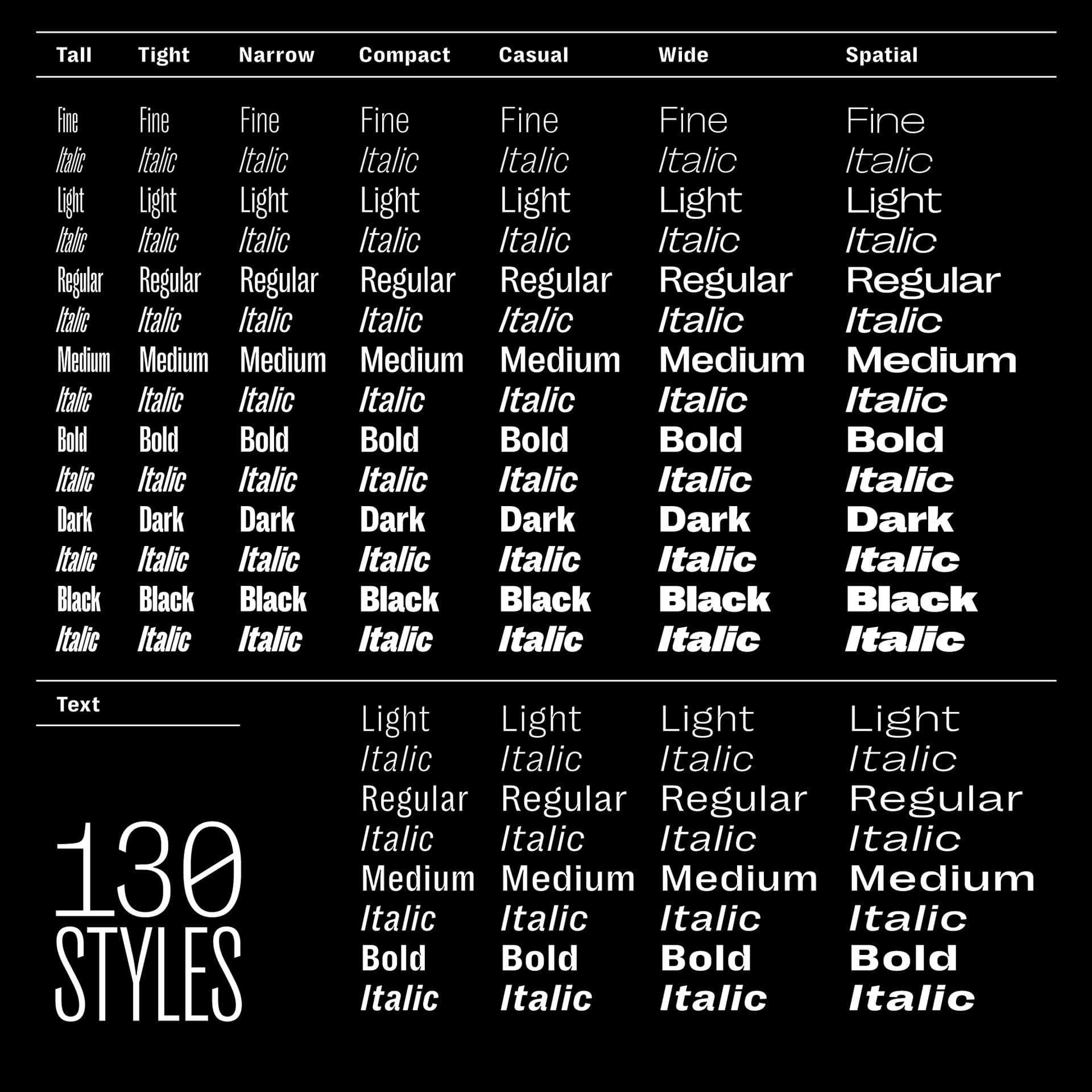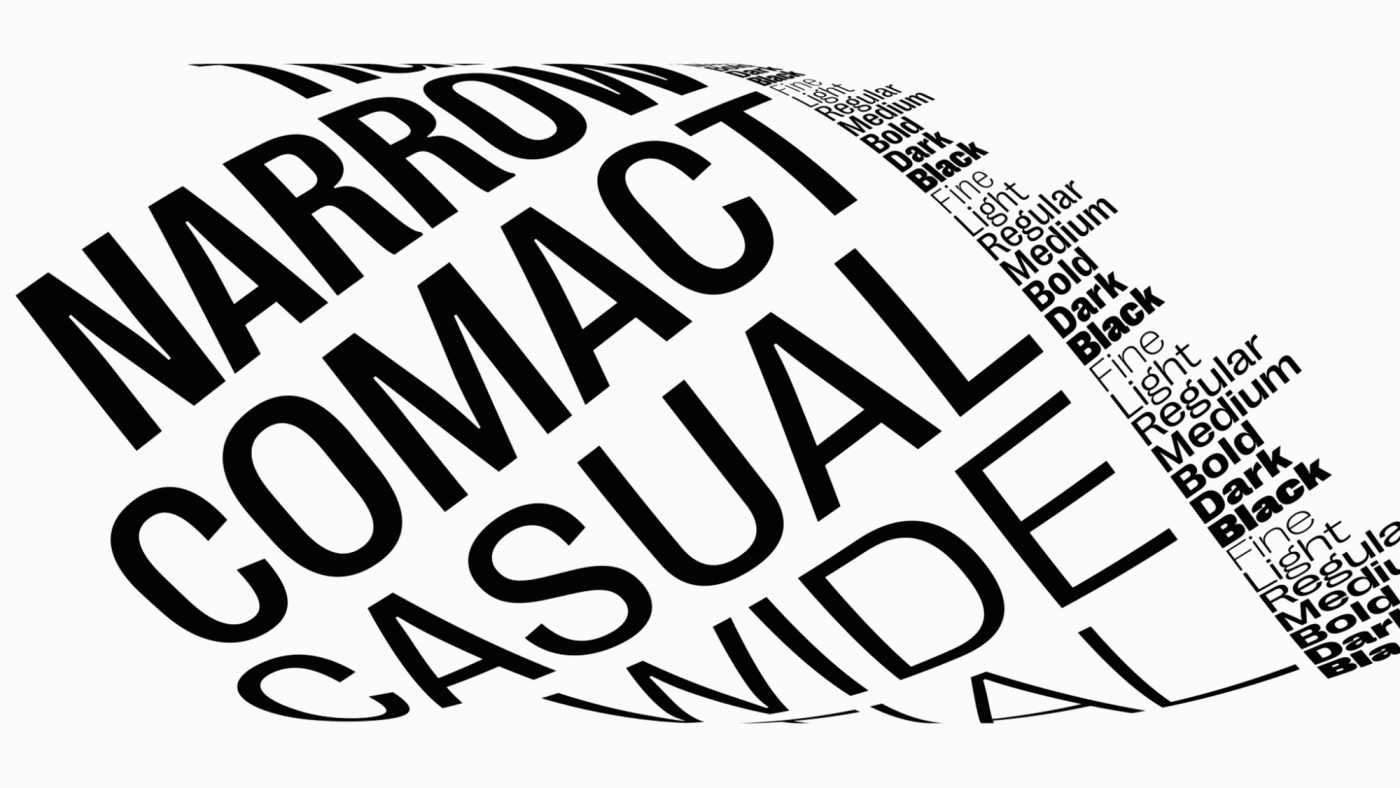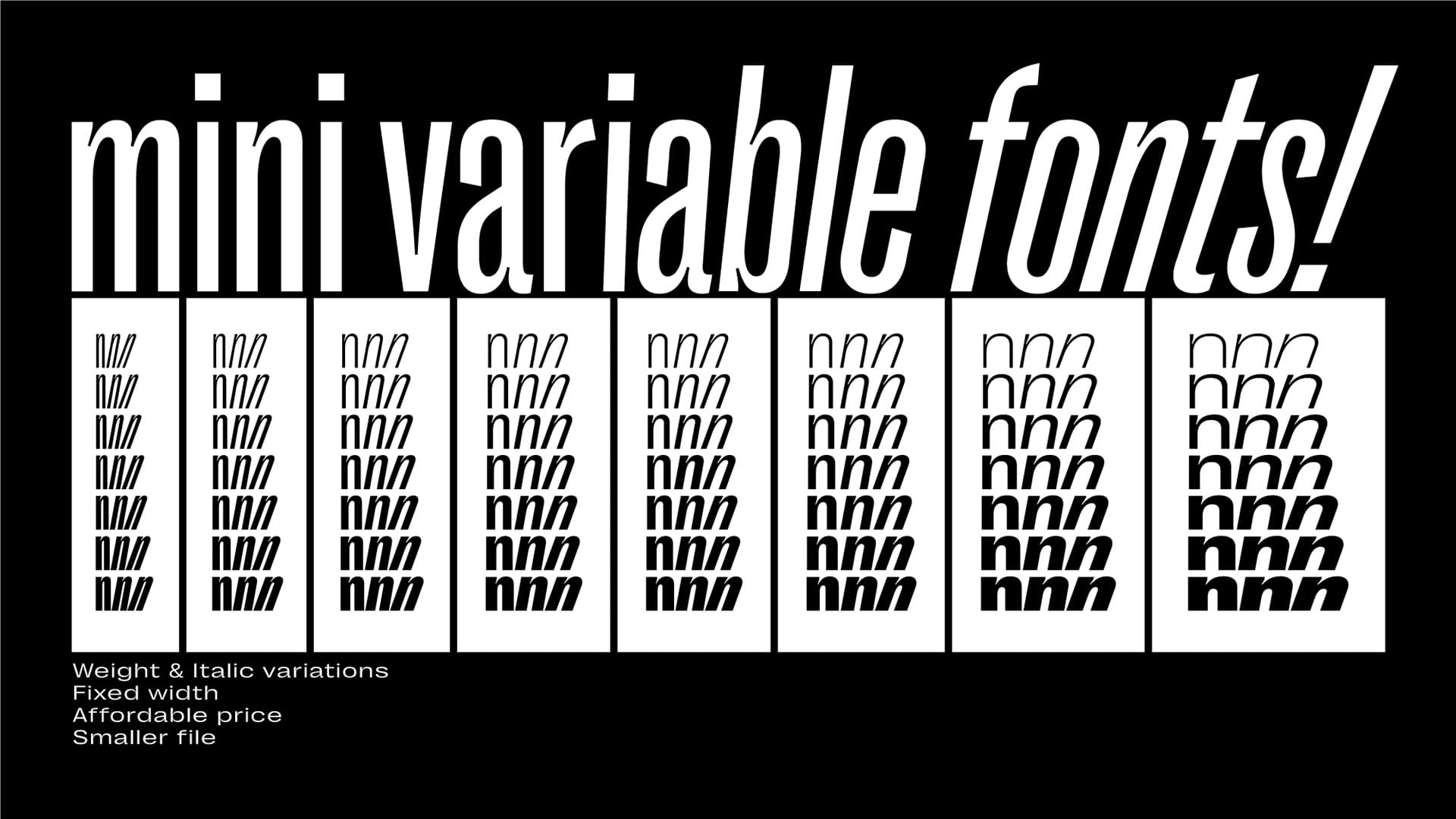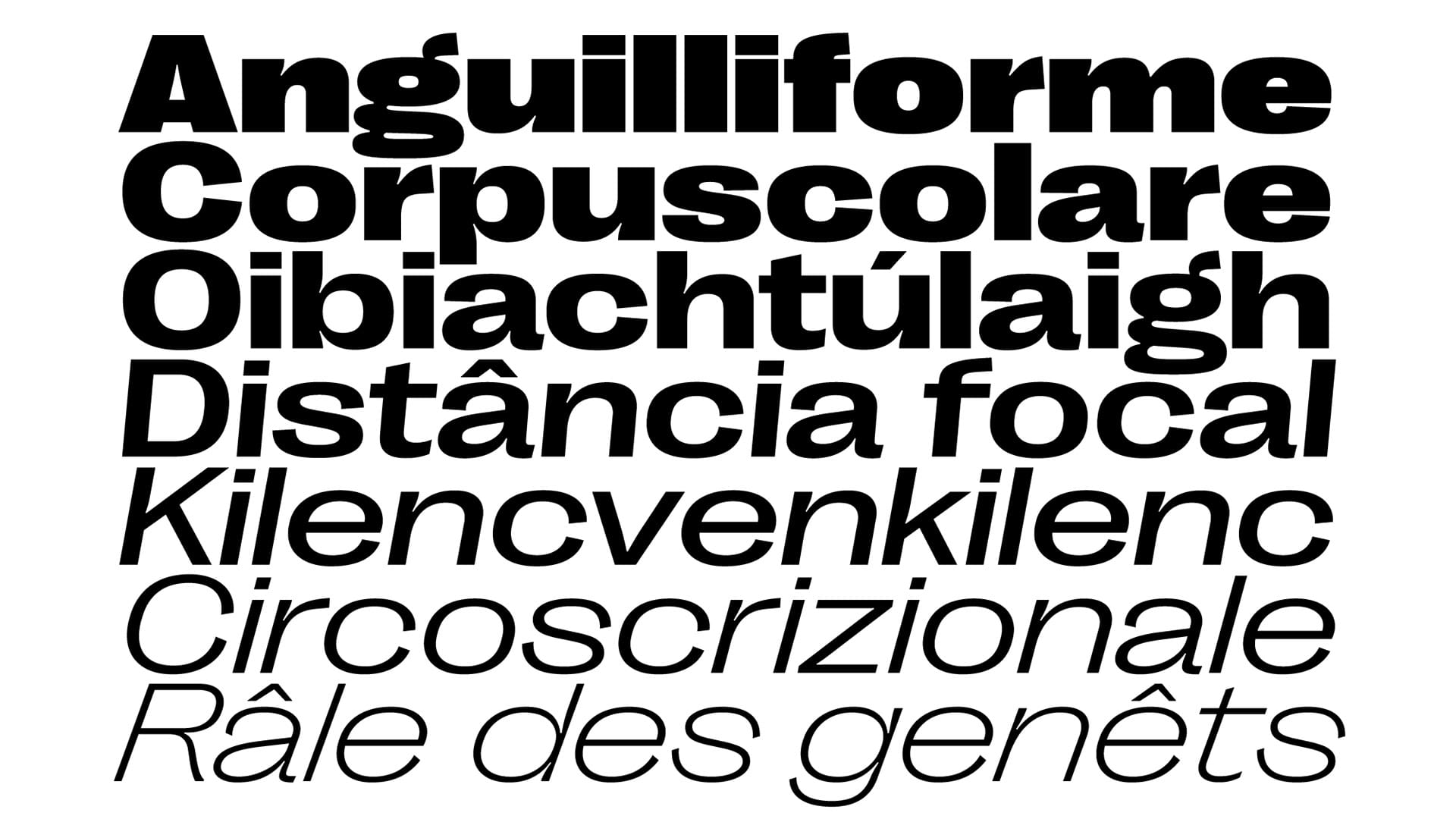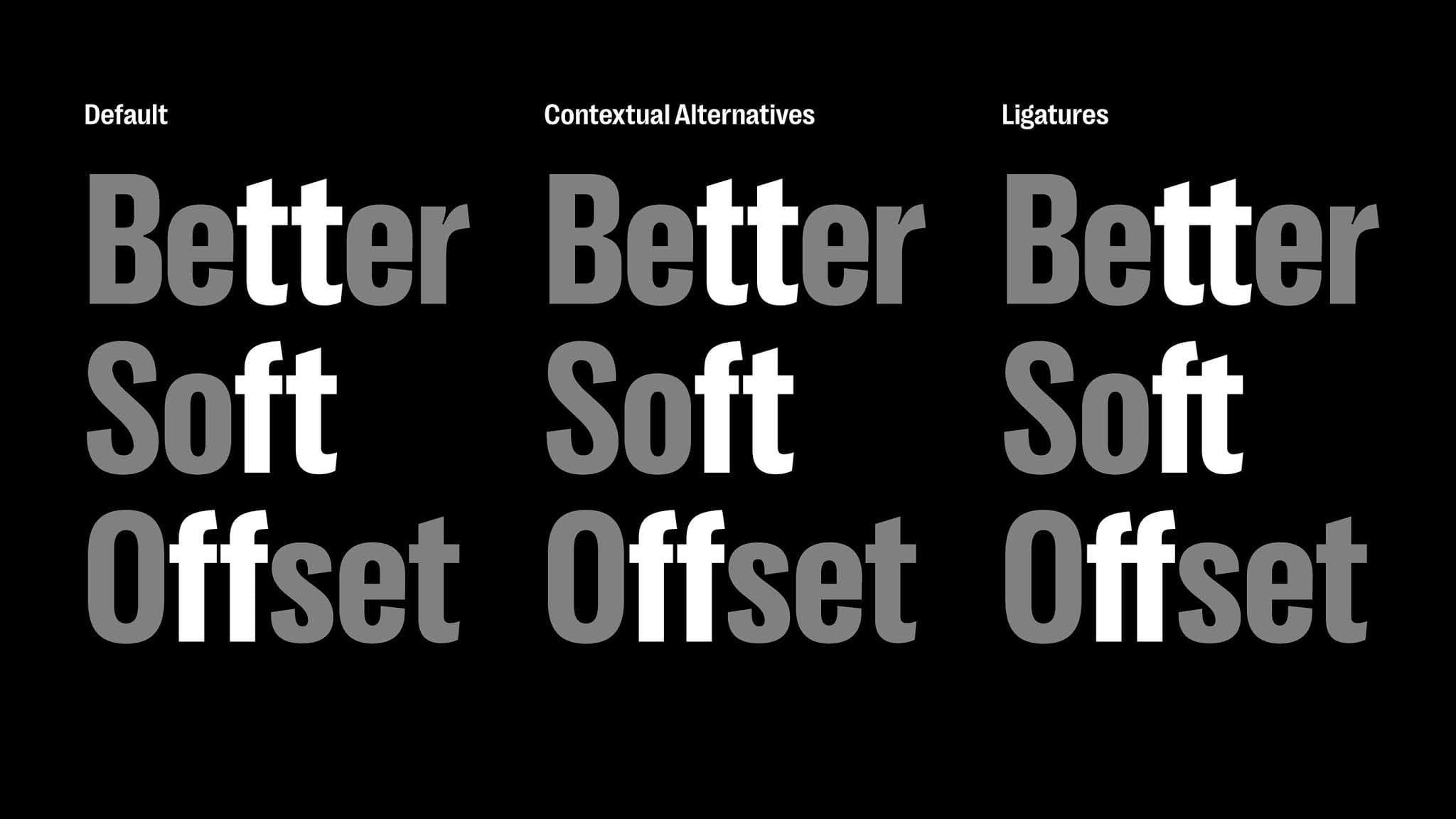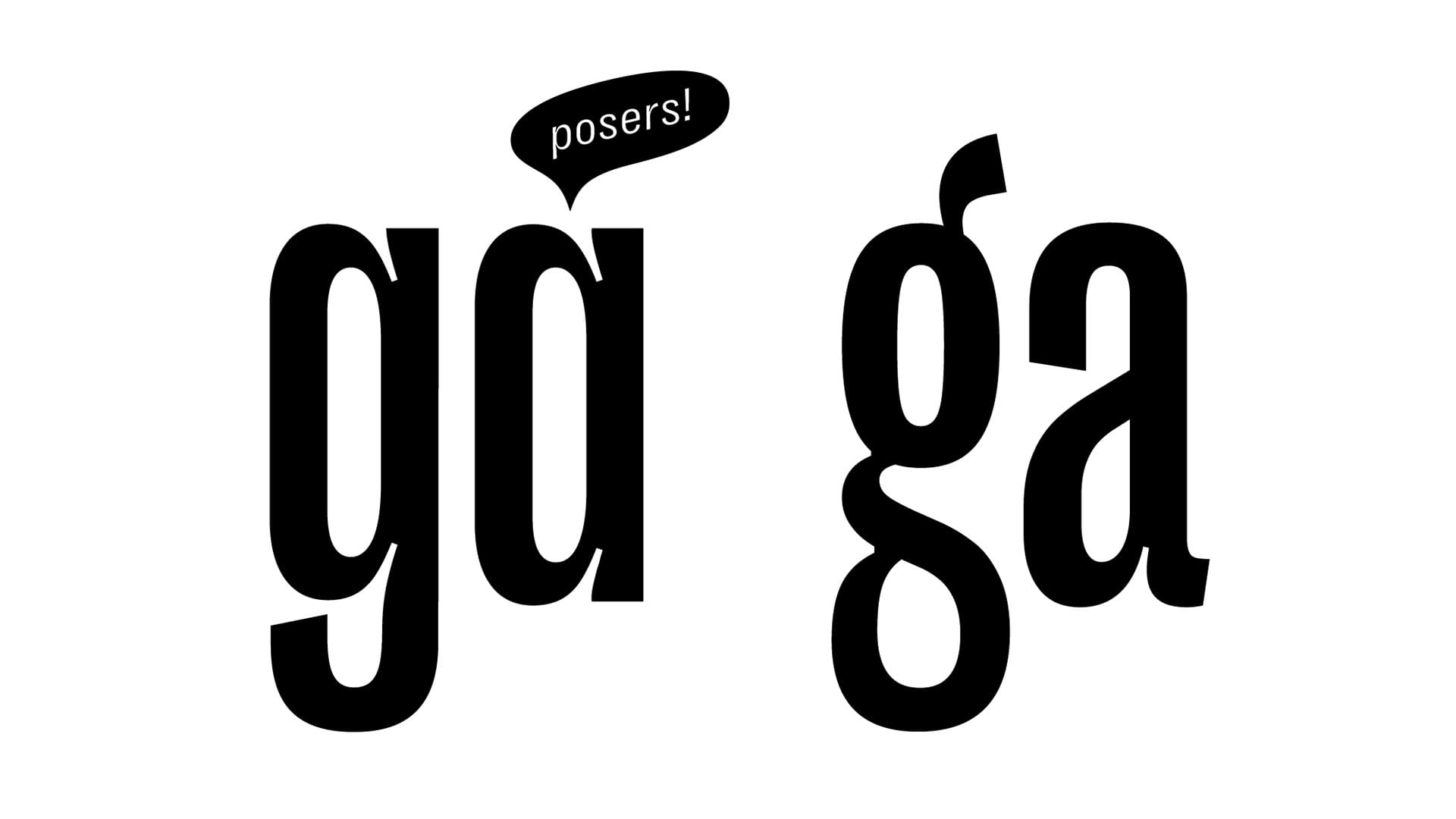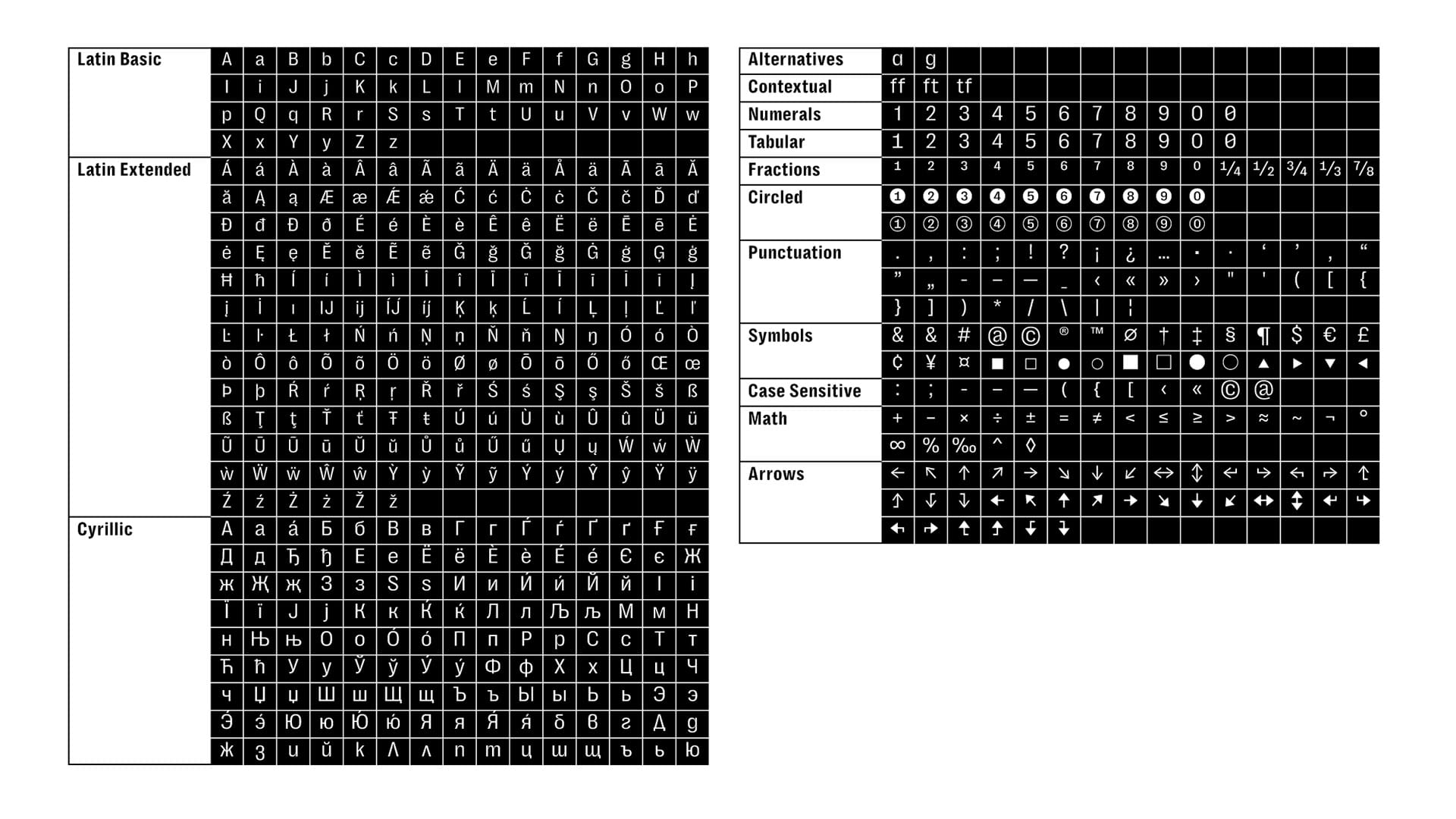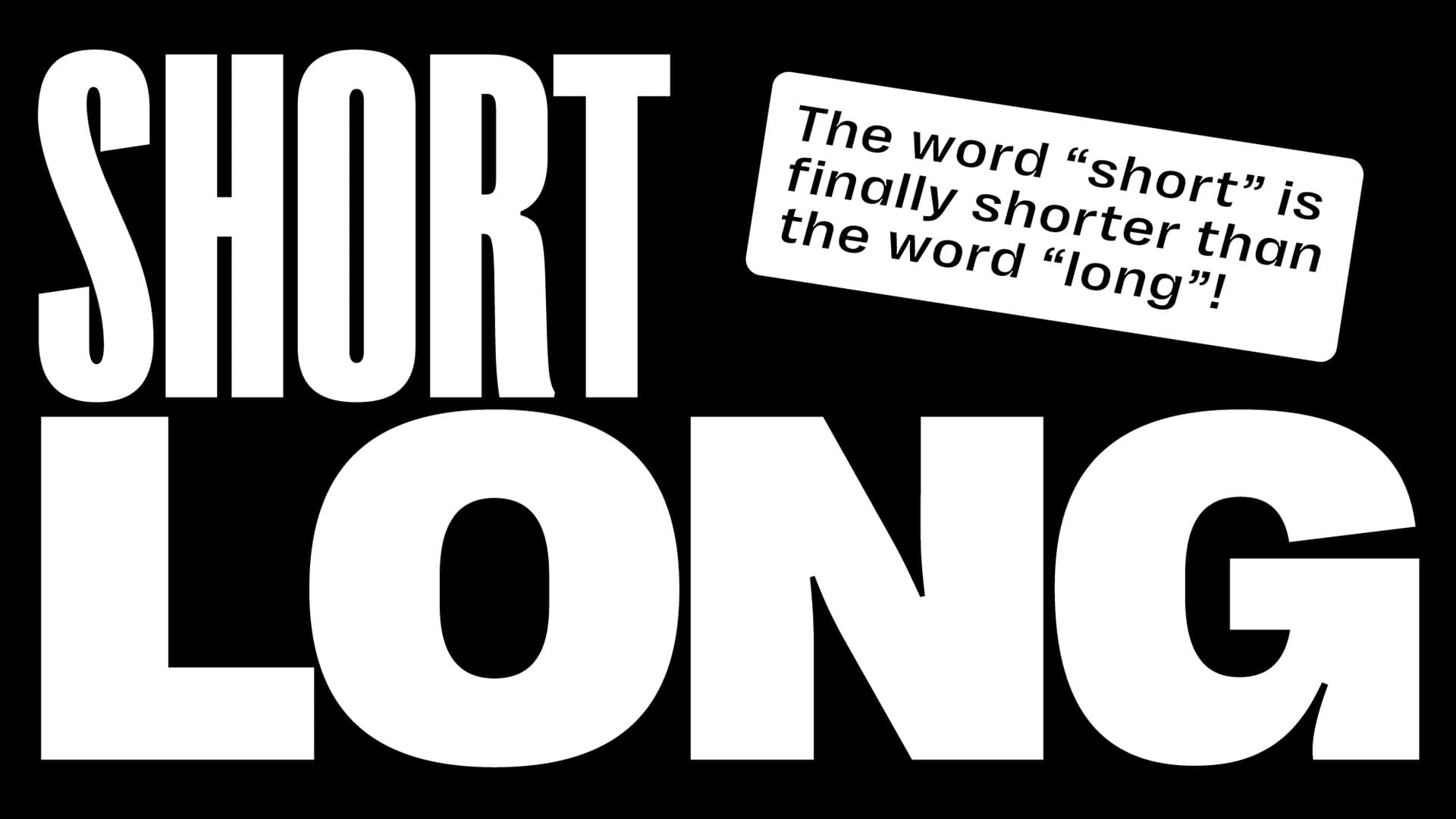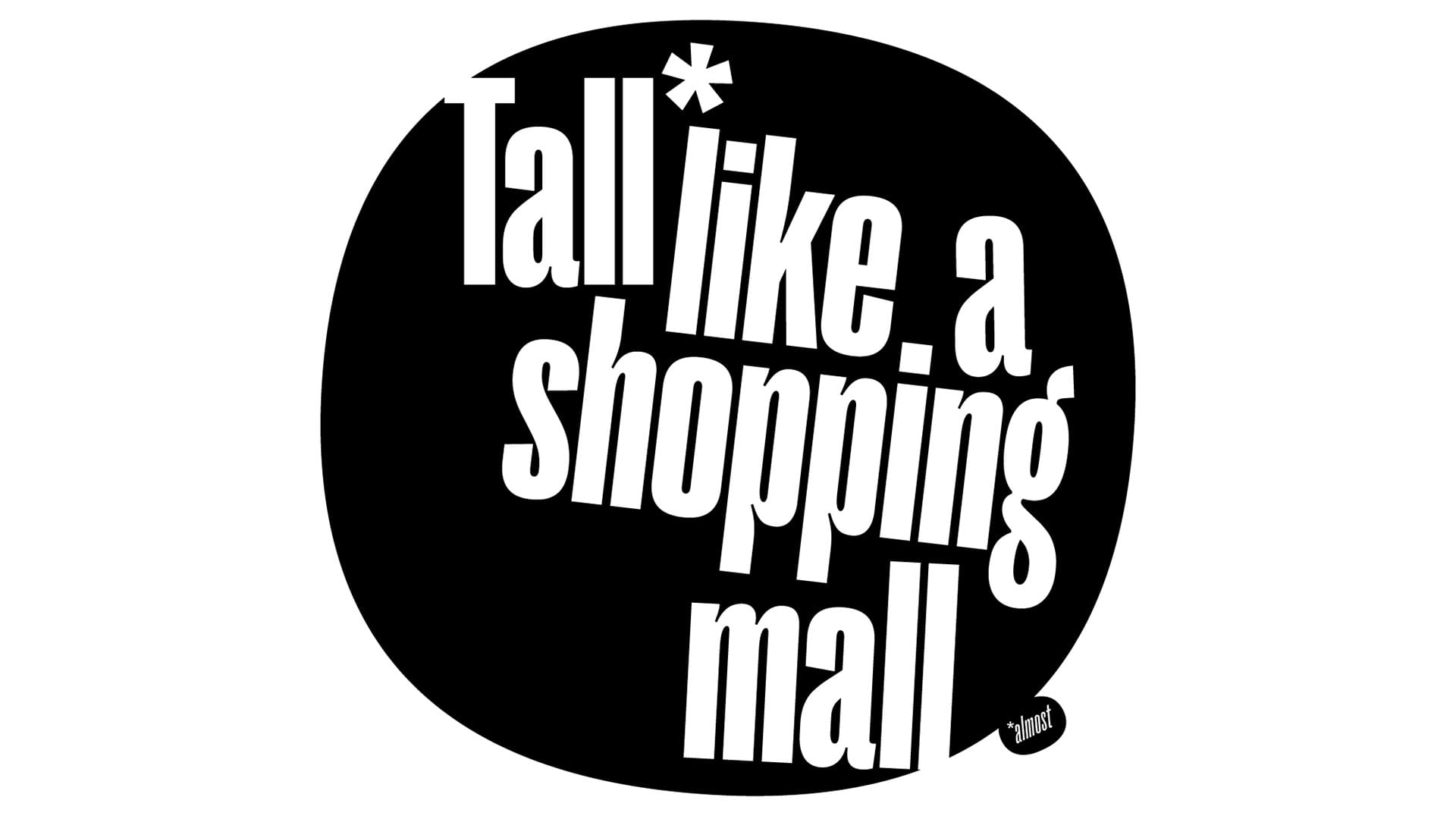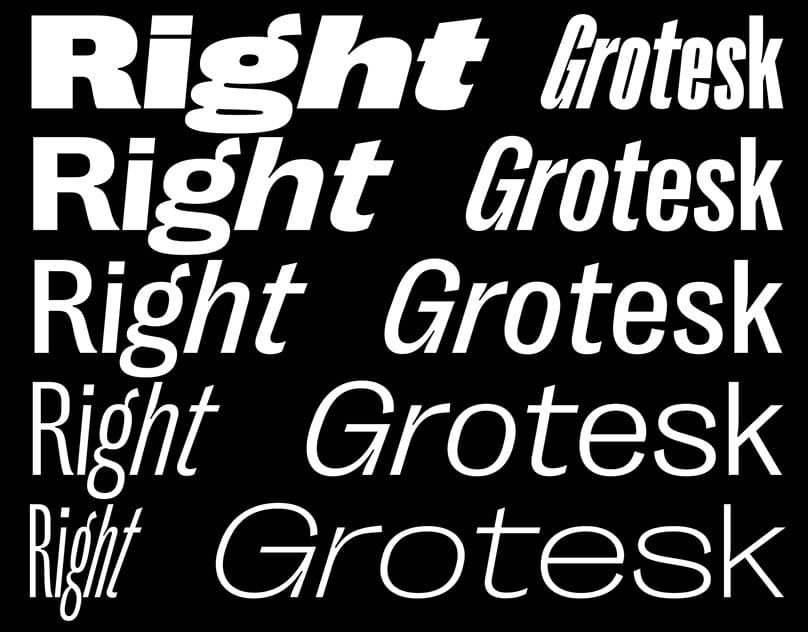
Right Grotesk Font Family bao gồm 51 kiểu với 545 glyph và hỗ trợ hơn 192 ngôn ngữ dựa trên latin. Font chữ Right Grotesk với các thiết kế ấn tượng và đặc biệt. Với nhiều chi tiết đẹp, đường cong mượt mà, độ tương phản vừa phải, kiểu chữ phù hợp với hầu hết các thiết kế của bạn.
Right Grotesk hỗ trợ khoảng 200 ngôn ngữ dựa trên Latinh và Cyrillic. Được thiết kế bởi Alex Slobzheninov.